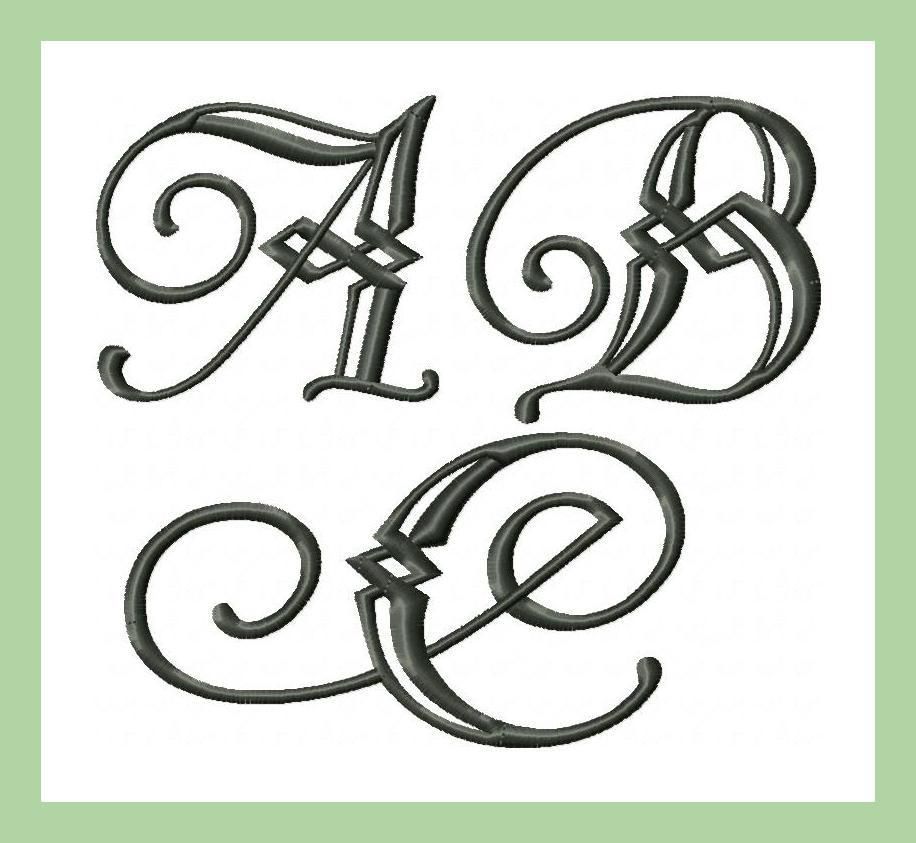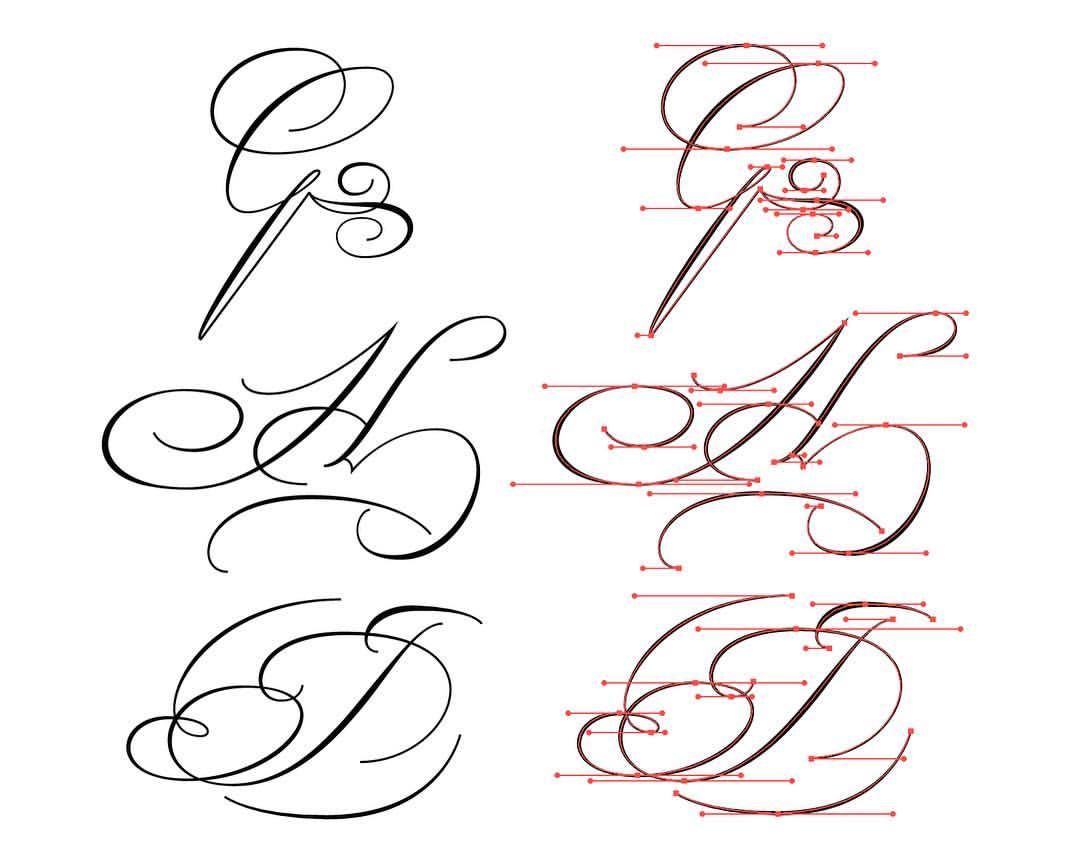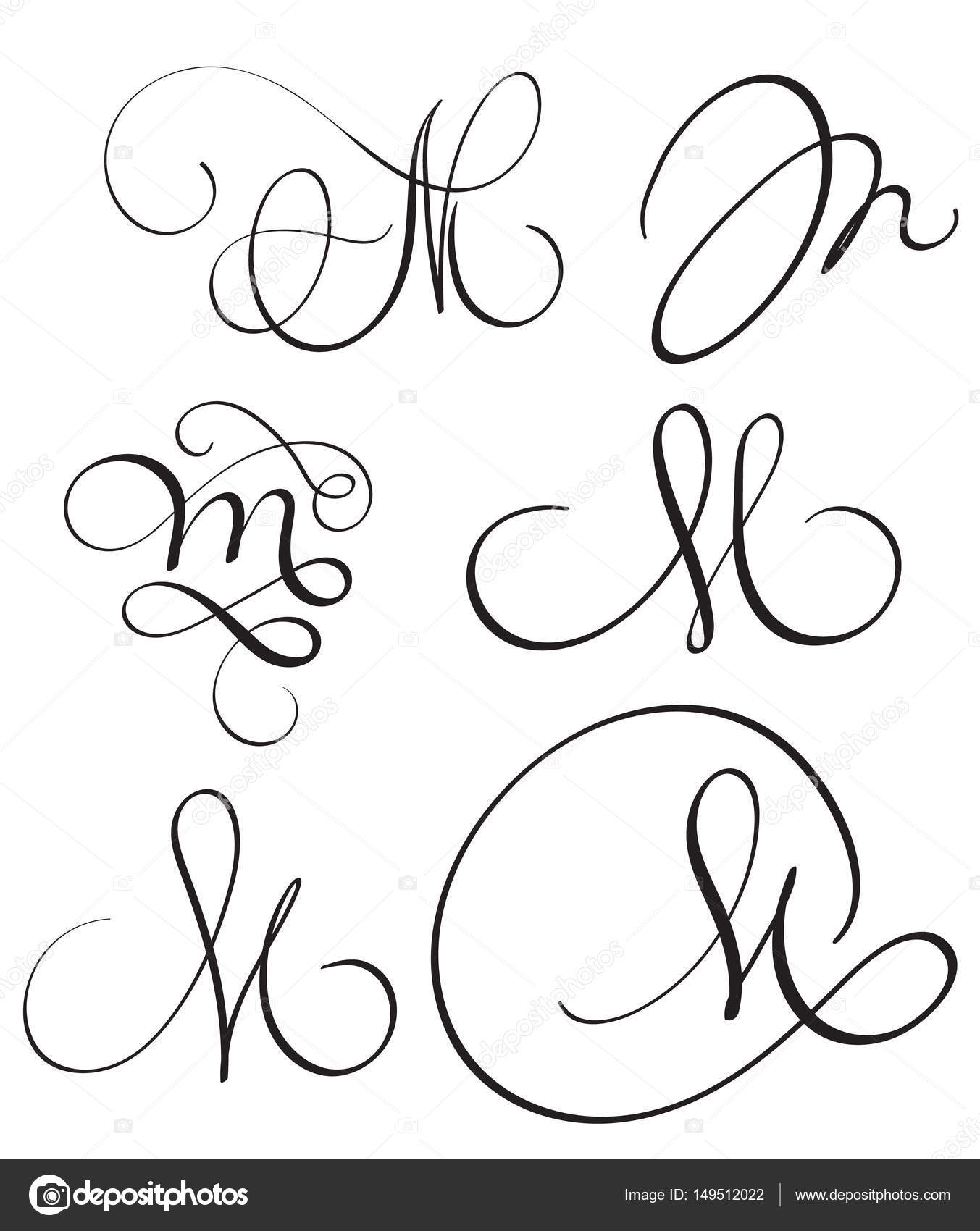
Каллиграфия и леттеринг для начинающих
Вы заинтересованы в изучении каллиграфии?
Если это так, то вы натолкнулись просто на идеальную статью, чтобы сделать это.
Изучение каллиграфии – непростой процесс, но с правильными методическими материалами это может занять меньше времени, чем вы думаете.
Что такое каллиграфия?
Этот термин заимствован из древнегреческого языка и означает искусство красивого письма.
Предполагается, что вместо того, чтобы просто писать красивые буквы, каллиграфы должны следовать ряду правил и традиций, в том числе тех, которые регулируют расположение и размещения букв в тексте.
Как освоить каллиграфию? Что еще более важно, действительно ли имеет смысл это сделать?
Например, если вы дизайнер, современная каллиграфия станет отличным навыком для добавления в ваше резюме и самым быстрым способом привлечения клиентов элегантными логотипами, знаками, карточками, приглашениями и т. д.
Наша статья о каллиграфии для начинающих поможет вам ознакомиться со всеми этими вещами и поможет вам в изучении каллиграфии, и даст вашей работе узнаваемый и индивидуальный стиль.
Вот наше компактное руководство по каллиграфии:
Изучение каллиграфии — с чего начать
Как научиться каллиграфии? Первый шаг на этом пути – взять правильное оборудование, в том числе лучшие каллиграфические ручки. Каллиграфия при помощи остроконечного пера потребует, чтобы вы научились пользоваться перьевой ручкой. В том числе такой, которая сделана из металлического наконечника – пера, и прикреплена специальным держателем.
Все подобные руководства по основам каллиграфии рекомендуют эти ручки, поскольку они не содержат чернил внутри и не могут нанести никакого ущерба – вместо этого вы окунаете их в специальный контейнер во время письма и извлекаете выгоду из их гибкости, чтобы экспериментировать с разными вариантами линий. Таким образом, ваше перо никогда не будет подвергаться коррозии и не засорится, несмотря на огромное количество различных чернил, которые вы должны использовать для завершения своего проекта.
Как использовать ручки для каллиграфии? Вот инструменты, которые вам понадобятся:
- Перья
- Держатели для перьев
- Бумага, подходящая для перьевых ручек
- Чернила
Перо
Новичкам, которые учатся как использовать каллиграфическую ручку, мы рекомендуем перо Nikko G-Nib. Оно относительно жесткое и рисует красивые линии с желаемым уровнем гибкости.
Держатель для пера
Существует два вида держателей для пера: прямой и косой (наклонный). Первый вид лучше подходит для вертикальных стилей каллиграфии, в то время, как наклонные держатели облегчают сочетание нескольких разных стилей.
Высококачественной и приемлемой по цене альтернативой является наклонный держатель для пера Speedball Oblique Pen Nib Holder, а также Tachikawa Comic Pen Nib Holder for Various Pen Nib – Model 25 (отличный выбор для вертикальных стилей, так как он держит крепче, чем другие аналогичные держатели).
Есть дизайнеры, которые используют один и тот же держатель для всех каллиграфических ручек, но мы советуем начинающим попробовать несколько разных вариантов прежде, чем выбрать один держатель.
Бумага
Шероховатость обычной бумаги не позволит вам использовать ее для каллиграфии. Среди других проблем вы столкнетесь с ситуациями, когда ваше перо цепляется за бумагу и оставляет раздражающие чернильные кляксы.
Кроме того, обычная печатная бумага имеет больше волокон и, следовательно, поглощает чернила и позволяет им распространяться внутри листа, что, вероятно, будет препятствием для гладких и чистых линий, к которым стремятся каллиграфы.
Чтобы сделать каллиграфию более эффективной и приятной, покупайте бумагу, которая подходит для перьев и перьевых ручек. Например, популярный бренд Rhodia, бумага которого очень гладкая и устойчивая к чернилам. Доступно несколько типов бумаги: чистые листы, в линию или с точечными сетками.
Чернила
Существует несколько типов чернил, подходящих для перьевых ручек, но новички всегда должны выбирать качественные черные образцы. Наш выбор – Speedball Super Black India, так как эти чернила очень темные, водостойкие, и в дополнение к этому по разумной цене.
Советы по подготовке
Как и любым творческим процессом, каллиграфией лучше всего заниматься в приятной рабочей среде.
Удобный и хорошо организованный стол, где вы можете разместить все свои принадлежности и чувствовать себя позитивно и расслабленно – лучшее место для отработки ваших навыков по каллиграфии.
Выбор лучшего места для работы
Чтобы извлечь максимум из практики по каллиграфии, выберите удобное и расслабляющее место, где вы можете удобно поставить ноги. Хорошо организуйте принадлежности и держите место не загромождённым, чтобы обеспечить достаточно пространства для движения руками.